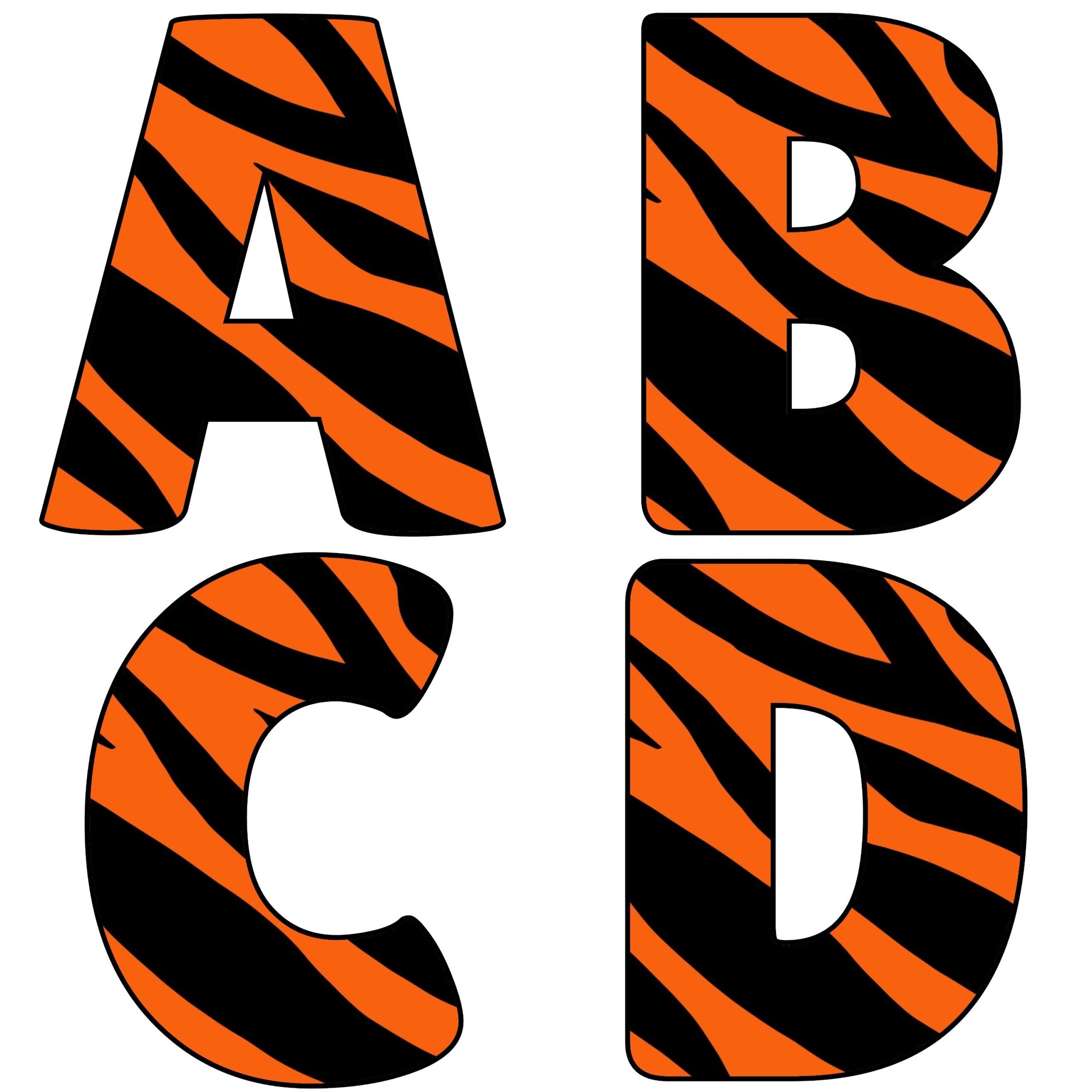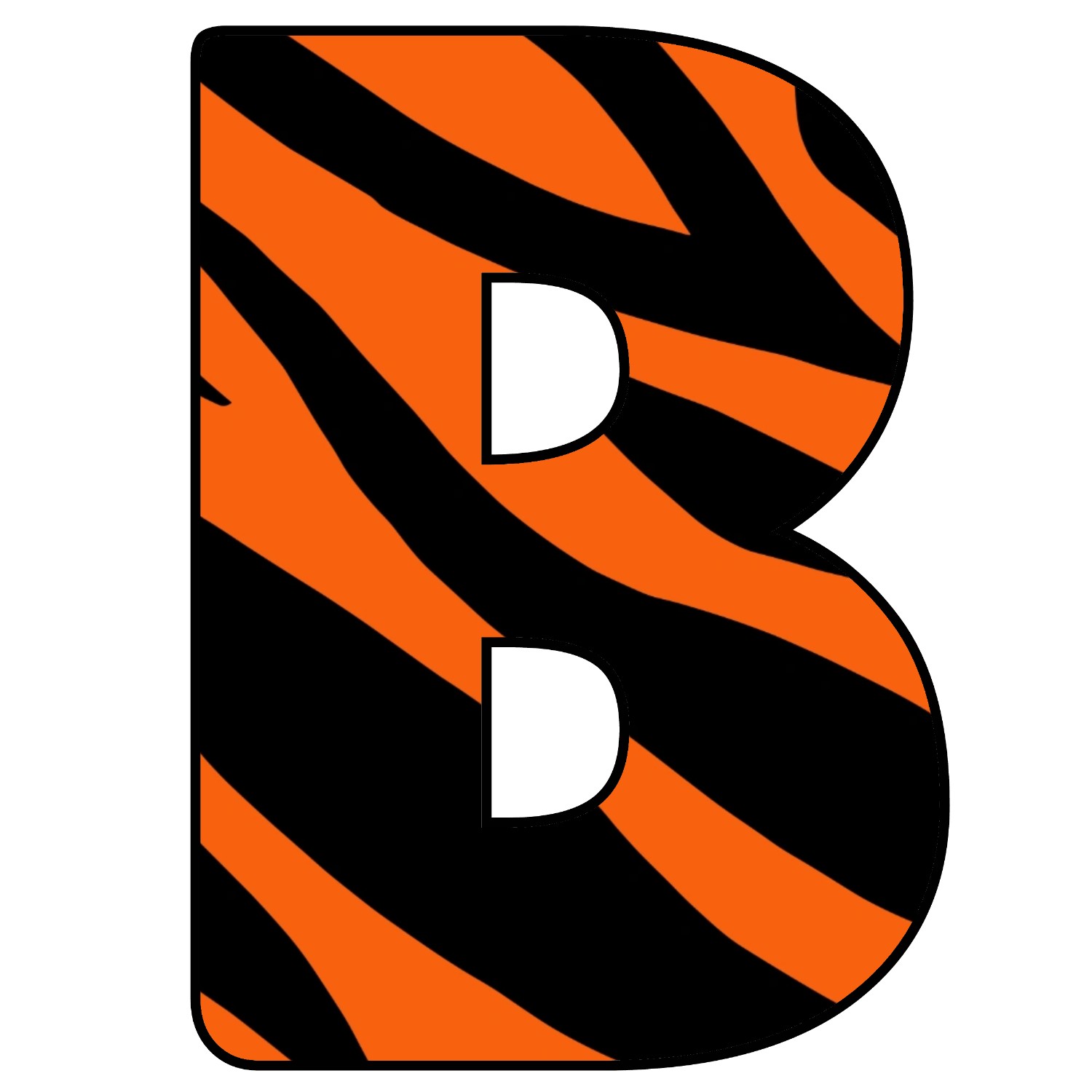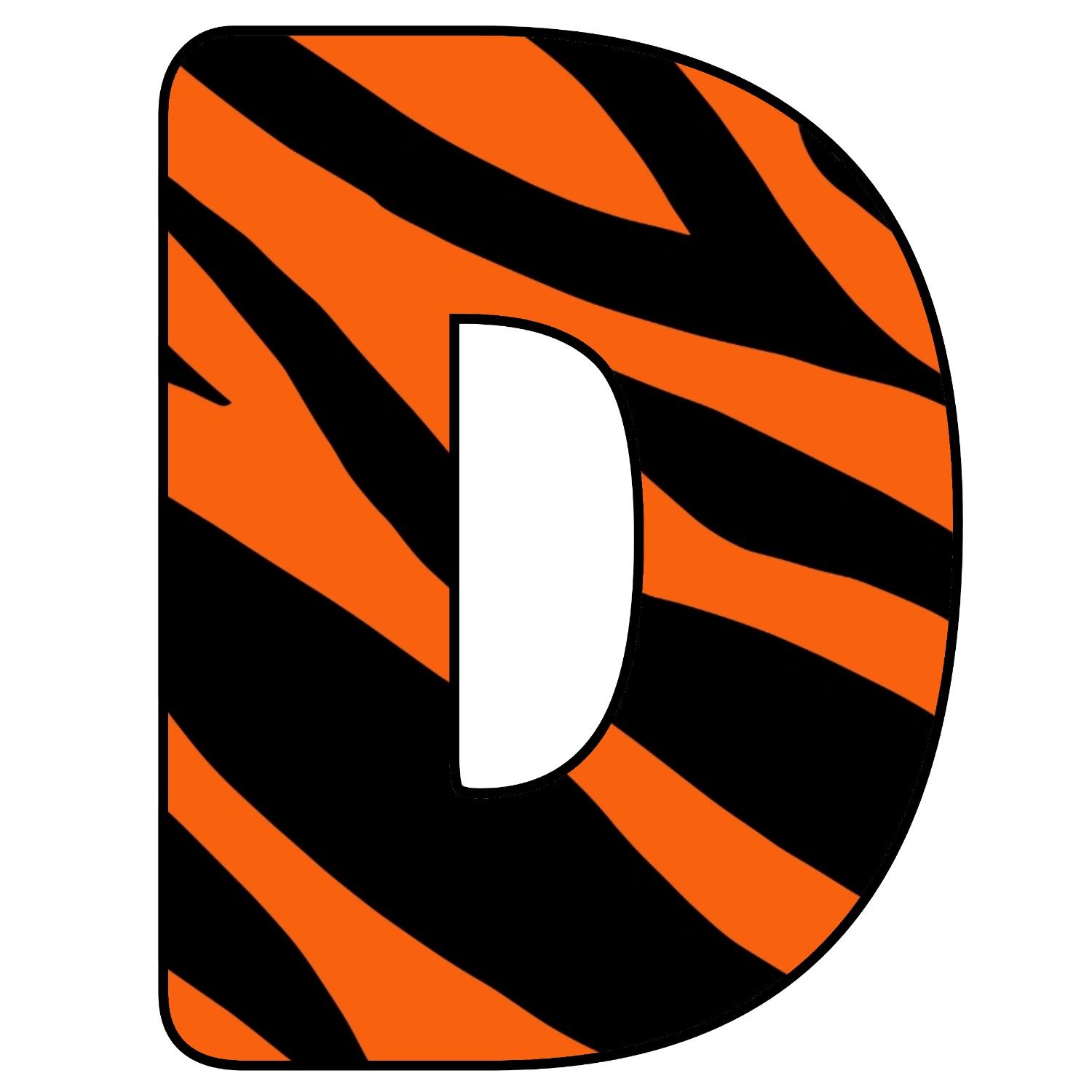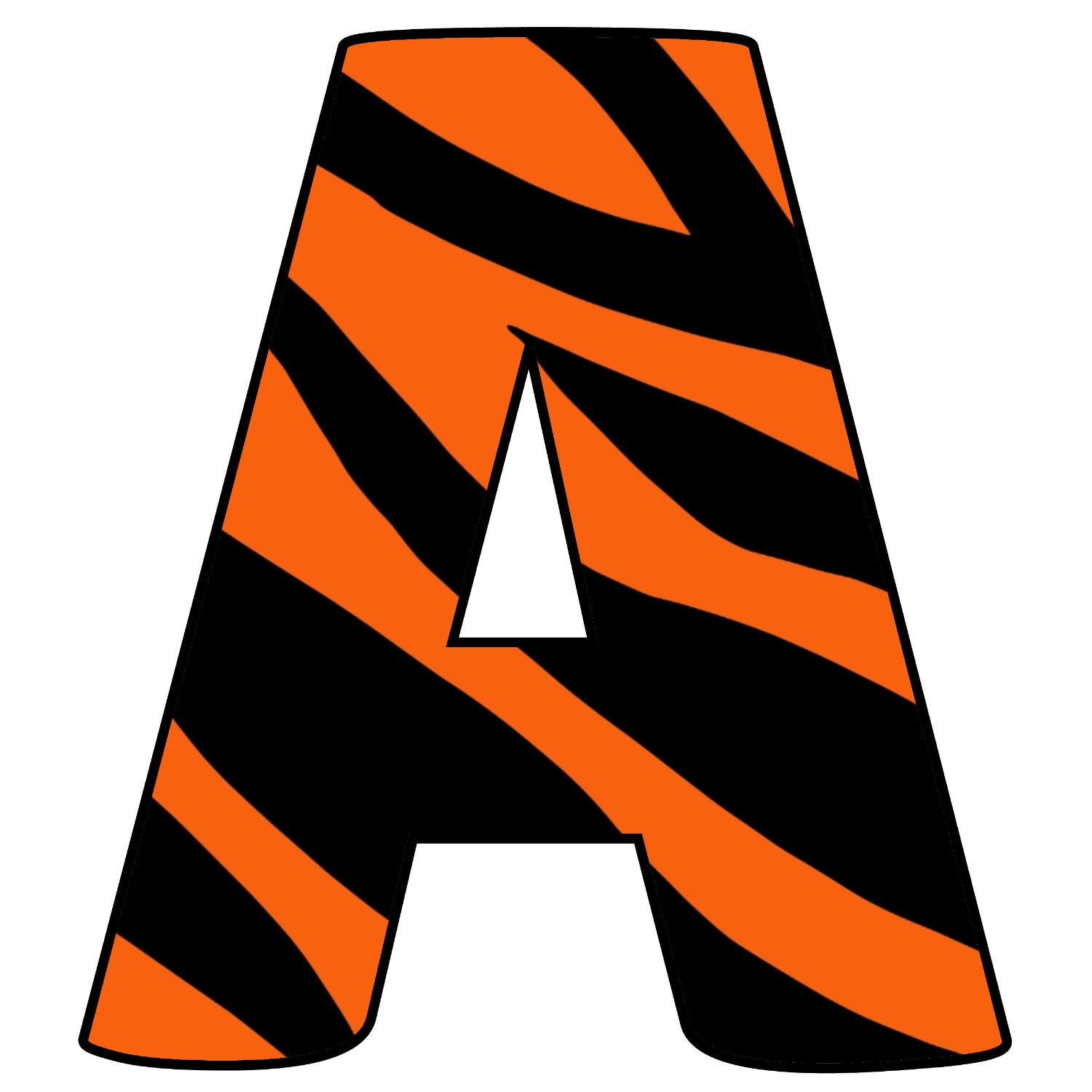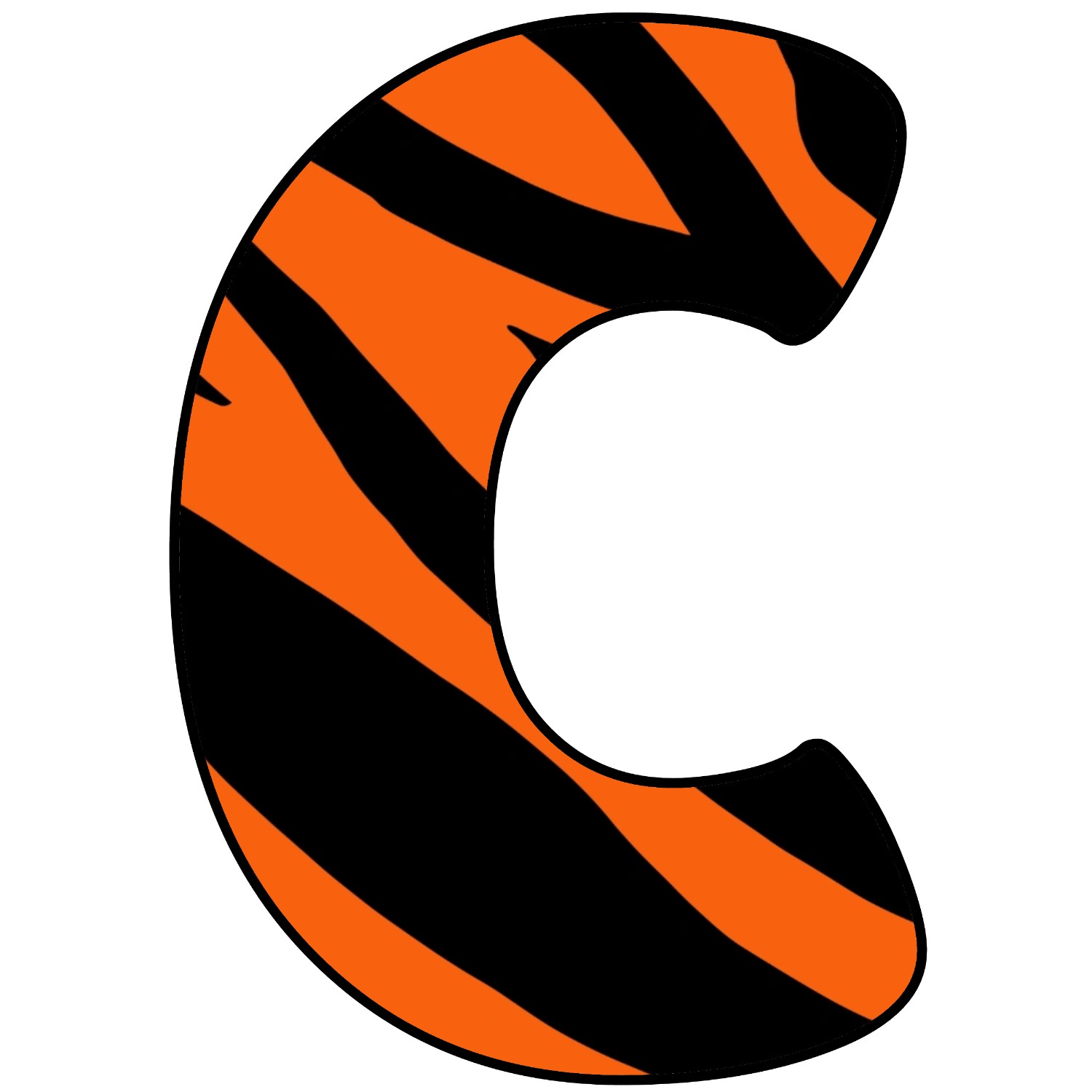
🔍Cada letra ha sido diseñada para que la impresión sea perfecta. Son ideales para crear guirnaldas con nombres, carteles de feliz cumpleaños, decorar salones de clase o cualquier proyecto creativo que tengas en mente. Gracias a su formato cuadrado y alta resolución, recortarlas es muy fácil y el resultado siempre es profesional.